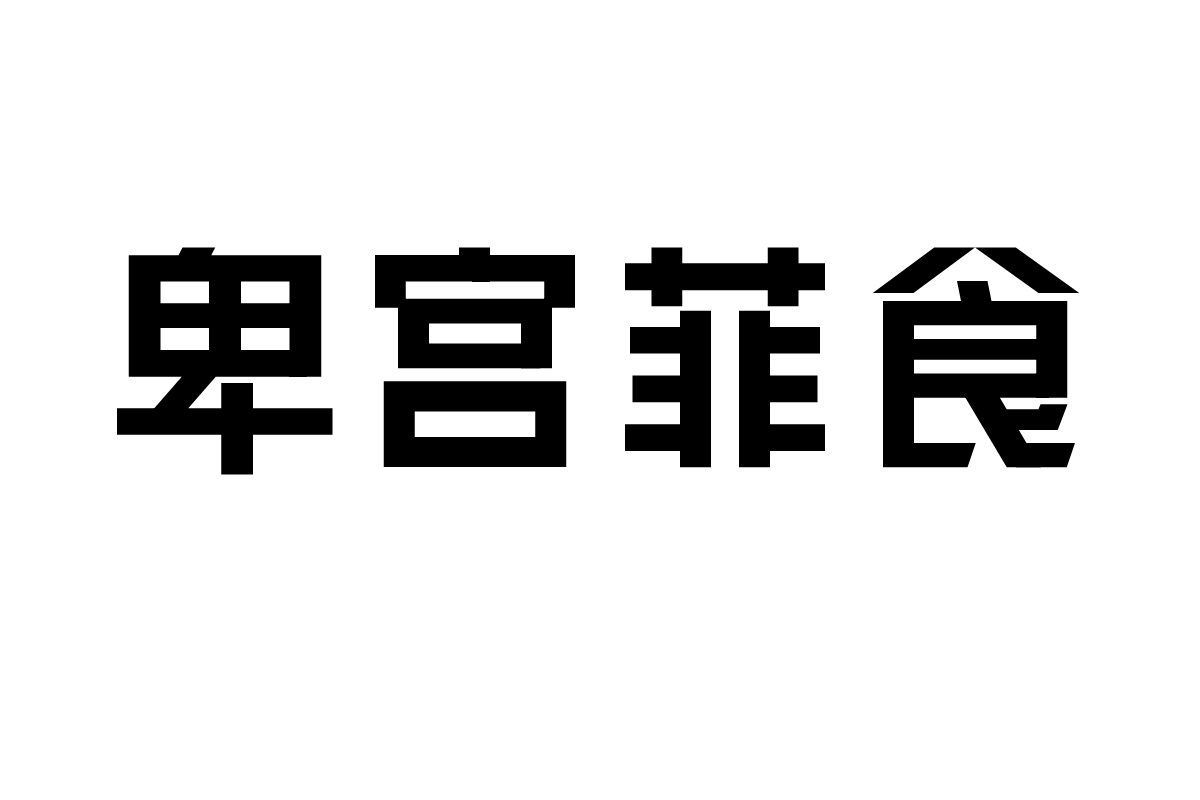
三极黑是一款由方正字库推出的中文简体字体,具有独特的风格和特点。这款字体的笔画粗细适中,线条流畅,给人一种稳重、大气的感觉。它的字形结构严谨,笔画规范,易于识别和阅读,适合用于各种文字设计场景。
三极黑字体的特点在于其中粗的笔画,使得整体视觉效果更加醒目。这种笔画粗细的变化,使得字体在视觉上呈现出一种层次感,既有力量感,又有美感。同时,三极黑字体还具有较好的可读性和易写性,适用于各种印刷和书写场合。
总的来说,三极黑是一款实用且美观的中文简体字体,适合用于广告、海报、书籍等文字设计领域。